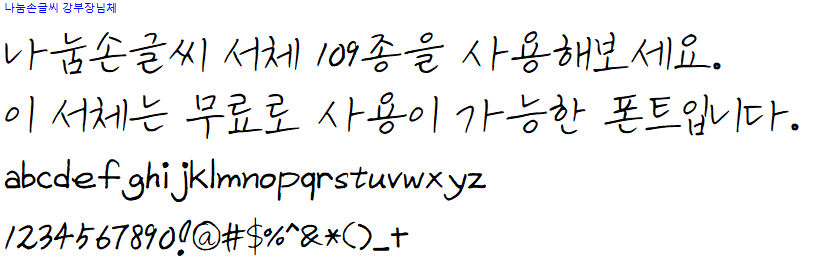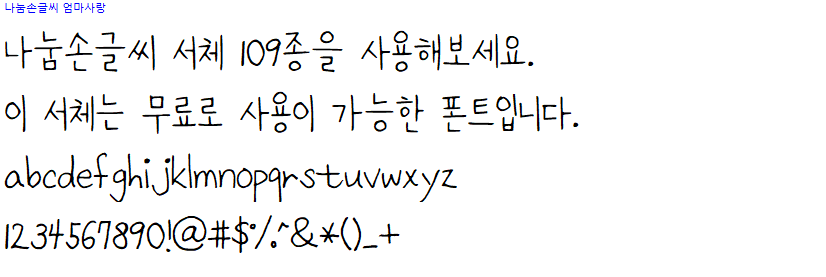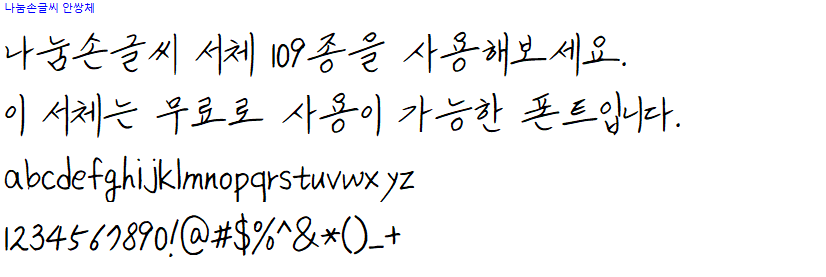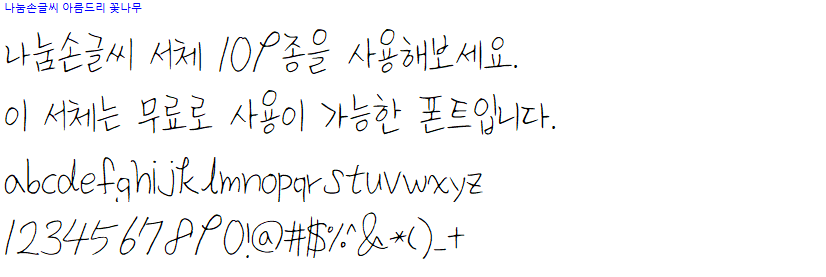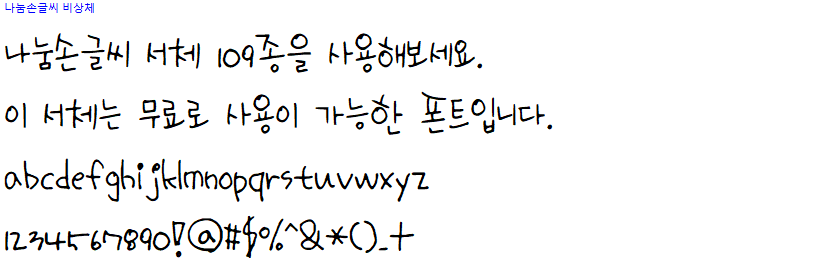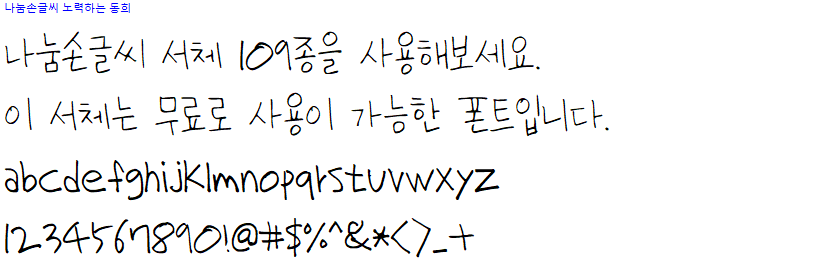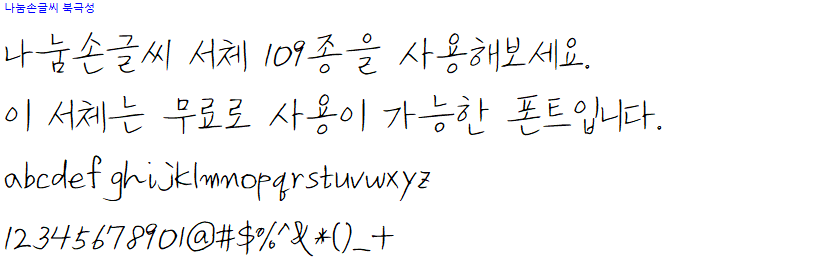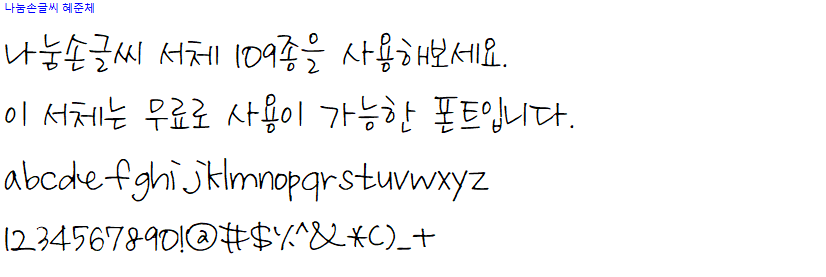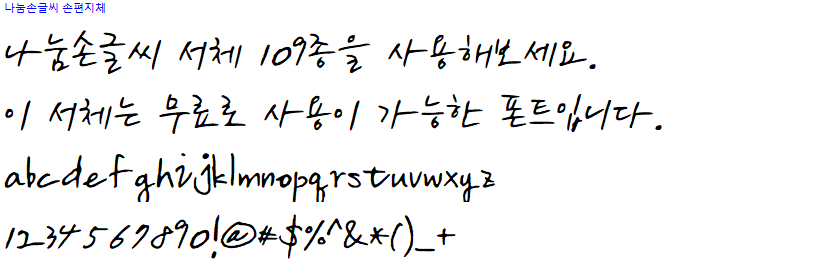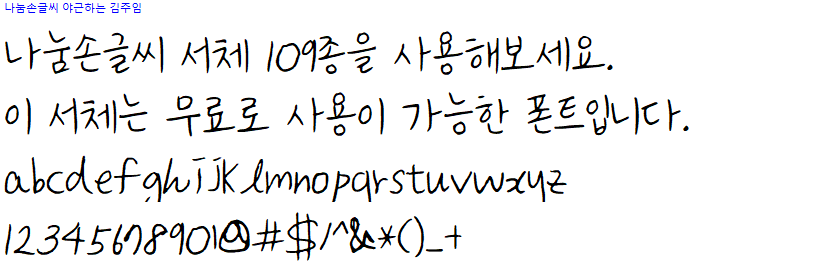
클로바 나눔손글씨폰트 전체 모음집 상업적 무료폰트
나눔손글씨 폰트
네이버의 클로바AI기술을 활용해 손글씨마다 가진 고유한 특징을 살려 글꼴로 제작하였습니다. 마음을 전하는 손글씨에 담긴 감성을 클로바 나눔손글씨로 느껴보세요. 저마다의 이야기를 담은 109종의 글꼴을 만나보세요.
다양한 손글씨 109종
나눔손글씨 가람연꽃
나눔손글씨 갈맷글
나눔손글씨 강부장님체
나눔손글씨 강인한 위로
나눔손글씨 고딕 아니고 고딩
나눔손글씨 고려글꼴
나눔손글씨 곰신체
나눔손글씨 규리의 일기
나눔손글씨 금은보화
나눔손글씨 기쁨밝음
나눔손글씨 김유이체
나눔손글씨 꽃내음
나눔손글씨 끄트머리체
나눔손글씨 나는 이겨낸다
나눔손글씨 나무정원
나눔손글씨 나의 아내 손글씨
나눔손글씨 노력하는 동희
나눔손글씨 느릿느릿체
나눔손글씨 다시 시작해
나눔손글씨 다진체
나눔손글씨 다채사랑
나눔손글씨 다행체
나눔손글씨 달의궤도
나눔손글씨 대광유리
나눔손글씨 대한민국 열사체
나눔손글씨 동화또박
나눔손글씨 둥근인연
나눔손글씨 따뜻한 작별
나눔손글씨 따악단단
나눔손글씨 딸에게 엄마가
나눔손글씨 또박또박
나눔손글씨 마고체
나눔손글씨 맛있는체
나눔손글씨 몽돌
나눔손글씨 무궁화
나눔손글씨 무진장체